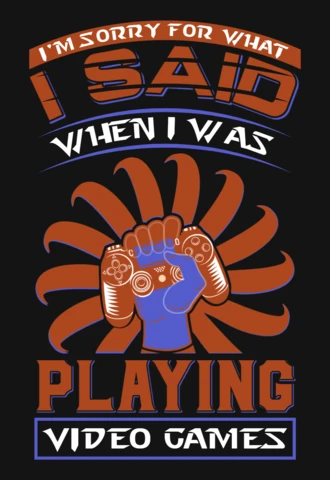
Modèle de typographie rétro : les jeux vidéo ne rendent pas violent
Les jeux vidéo ne rendent pas violent, le décalage n'est pas le cas des jeux vidéo